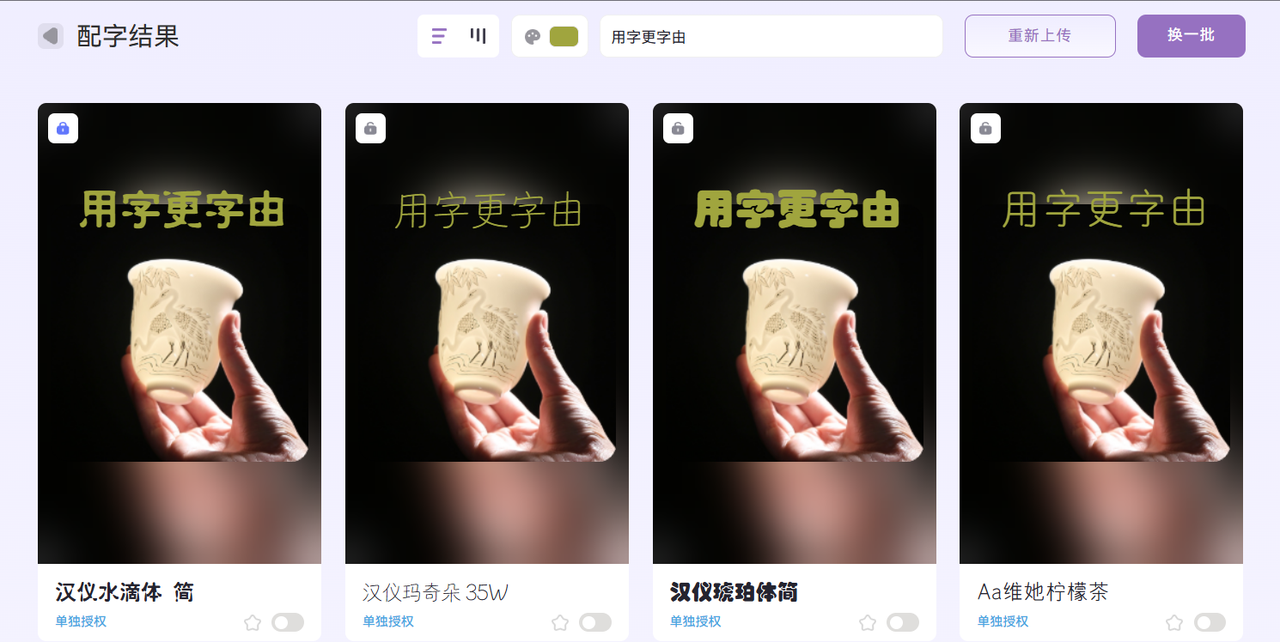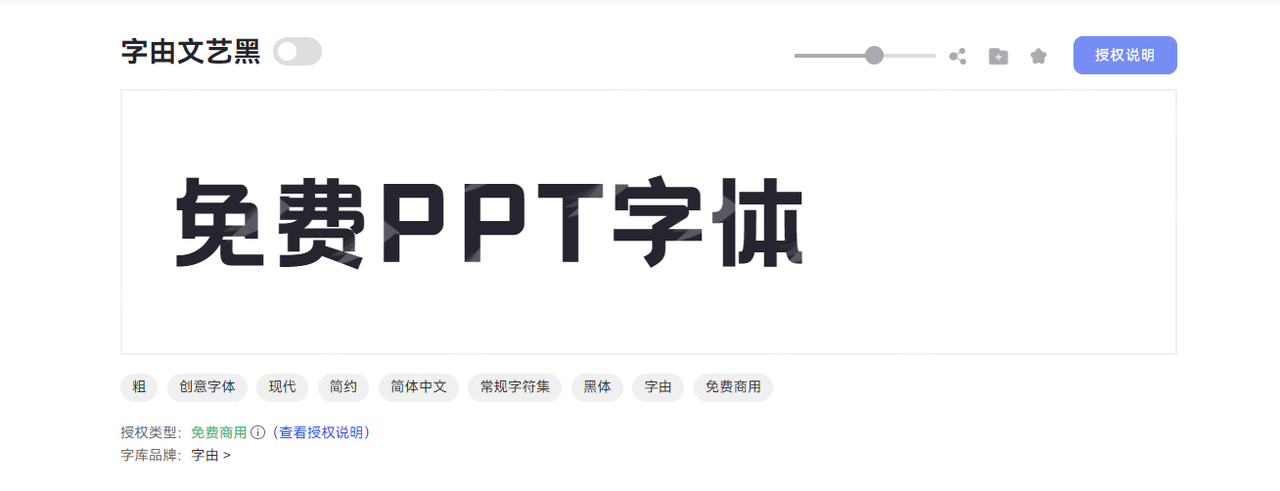
免费 ppt 字体哪里找?6 个高质量字库赶快收藏!
有没有工作中经常需要用到 PPT 的小伙伴?你们是否每次也会头疼怎么能找到默认字体之外的免费 PPT 字体?我们都知道,一款好看且合规的 PPT 字体是提升演示效果的关键因素,和 PPT 主题高度匹配字体会让人看起来更加舒适且有足够的吸引力,候系统自带的字体并不能很好地满足制作 PPT 的需求。不用担心!接下来介绍的这 6 个高质量免费 PPT 字体库赶紧收藏起来备用,涵盖了复古优雅、商务简约、潮酷朋克、创意手写等多种风格,帮助你制作更加高质量且出彩的 PPT。
一、字由
字由是面向设计师用户提供字体应用,管理,授权服务,注册用户超 2000 万的必备字体工具。字由客户端集成了 1000+ 字体厂商公开授权免费商用字体,适合 PPT 的字体也不在少数,保证你用字无忧。
而且字由支持在 PS、AI、ID、XD、Figma、Sketch、CDR 等设计软件中一键应用字体,无需下载,安装字体包,不占用系统内存,即可完成字体应用。
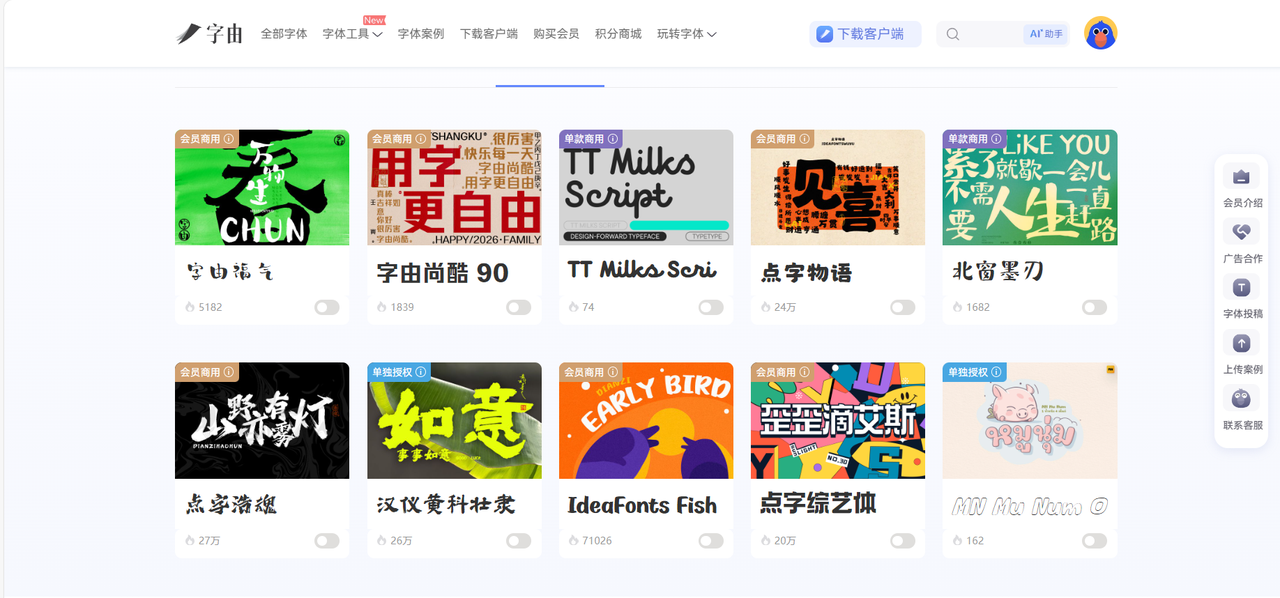
有一个功能是我要强烈推荐的——AI 配字,可以帮助新手小白的你快速选择适合 PPT 风格的免费字体。用户只需上传一张图片,即可通过 AI 识别图中元素,并从海量字体数据中,推荐适合该图片的字体,同时支持对文字样式进行自定义编辑,助力设计师创作。
- 推荐字体:字由文艺黑
字由文艺黑是字由品牌推出的创意黑体字体,以现代简约风格为核心,将图形设计法则巧妙融入黑体设计。字体字形方正饱满,既保留黑体的稳重基调,又通过优雅的艺术弧线处理增强视觉张力,让整体结构充满平衡感与力量感。字由文艺黑笔型设计独具特色,以利落直角勾勒轮廓,搭配方头笔画与均匀粗细,笔画连接采用断开处理,既保持线条的独立性,又让字形更显灵动透气。作为免费商用字体,字由文艺黑字符集覆盖常规中文,适用于商务、党建、科技等风格的 PPT,可以用作年终汇报或者是一些正式的场合,是现代设计中追求文艺感与商业价值的理想选择。
二、DaFont
DaFont 是全球知名的一个免费字体平台,内含 10 万种字体,覆盖了复古、手写、涂鸦、可爱等多种风格,主要提供创意手写体的风格。我觉得 DaFont 的分类是真的很详细,按照风格、主题、语言等多个维度对字体资源进行划分,让你能更快地找到想要的 PPT 字体。或许是因为该平台的字体数量过多,它的质量参差不齐,如果你想要优质的 PPT 字体,得自己好好筛选一下哦。
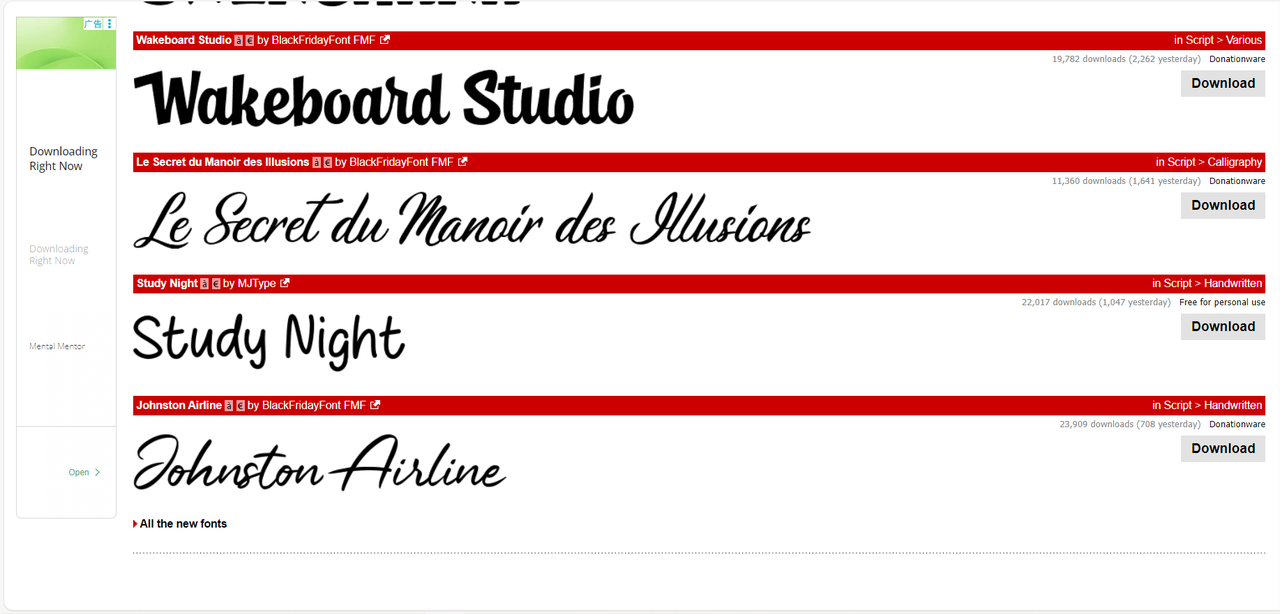
三、Font Squirrel
一直在找商用 PPT 字体的设计师小伙伴们一定要记好了!Font Squirrel 提供大量可商用的免费字体,所有字体均是经过授权审核的,确保可以免费用于个人/商用项目。值得一提的是,Font Squirrel 提供字体下载、Web Font 转换、子集化(减少文件大小)等服务,有需要的用户可以慢慢研究。相较于上面提到的 DaFont,它的字体数量相对较少,只有 1000 种左右,但字体质量更高,设计感很强,不过中文字体选择有限,更倾向于提供英文 PPT 字体。
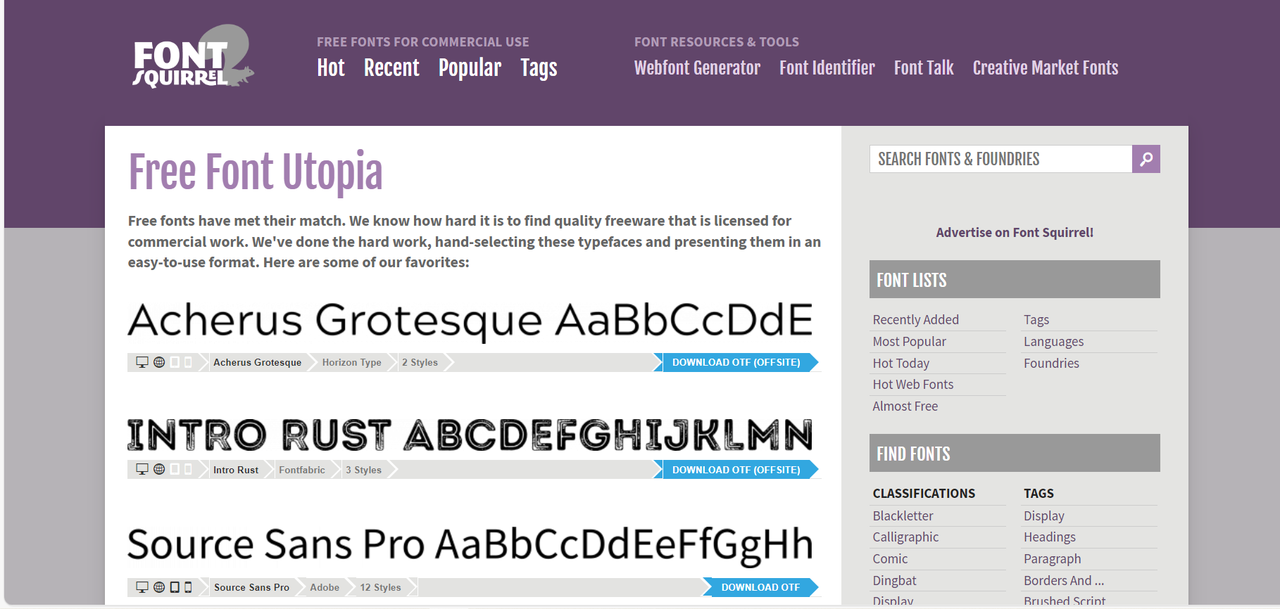
四、Google Fonts
Google Fonts 是谷歌推出的全球最大的开源字体库,所有字体均遵循开源协议,可免费用于个人/商用 PPT 设计,无需付费或授权,还支持直接嵌入 PPT 或本地安装。它拥有中文/英文字体的专区,用户可以根据需求来选择。Google Fonts 的字体筛选一直是我用起来顺手的,根据类别、语言、风格、线条粗细、倾斜角度、字宽的维度来搜索字体,定位更清晰准确,便于快速锁定字体。不过它提供的字体都比较简约日常,如果需要设计感强的字体,这个字库可能不太适合你哦。
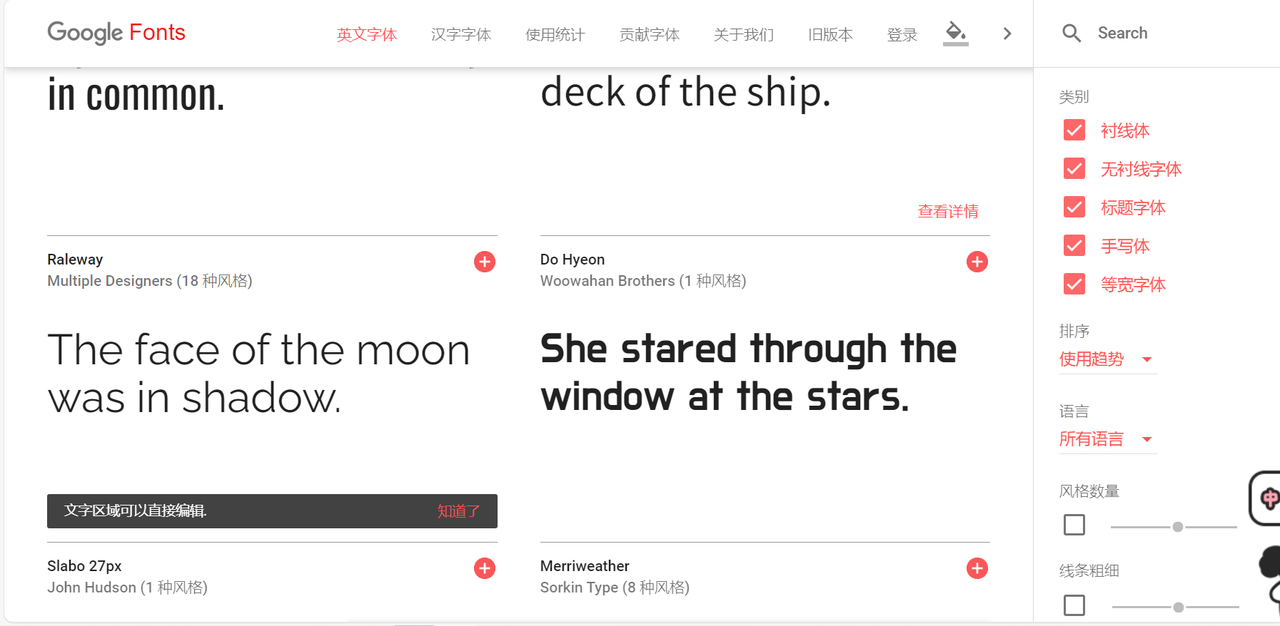
五、Fontspace
Fontspace 也是非常专业的免费商用字库,支持本地安装及 Web Font 使用,可按风格、语言筛选 PPT 适配字体。它专门为涂鸦字体设置了一个版块,包含滴水、纹理、融化、油漆、摇滚等风格,文字效果贴近在城市墙壁、公共建筑等地方的喷涂艺术效果。你的 PPT 做的是和涂鸦艺术、潮酷设计相关的领域,不妨来 Fontspace 找找合适的字体。除此之外,它还设有设计师社区,根据每个设计师的字体被下载数量形成了排行榜,不知道要选择什么类型的字体,可以根据排行榜看看当下比较热门的哦,说不定能提供一些灵感。
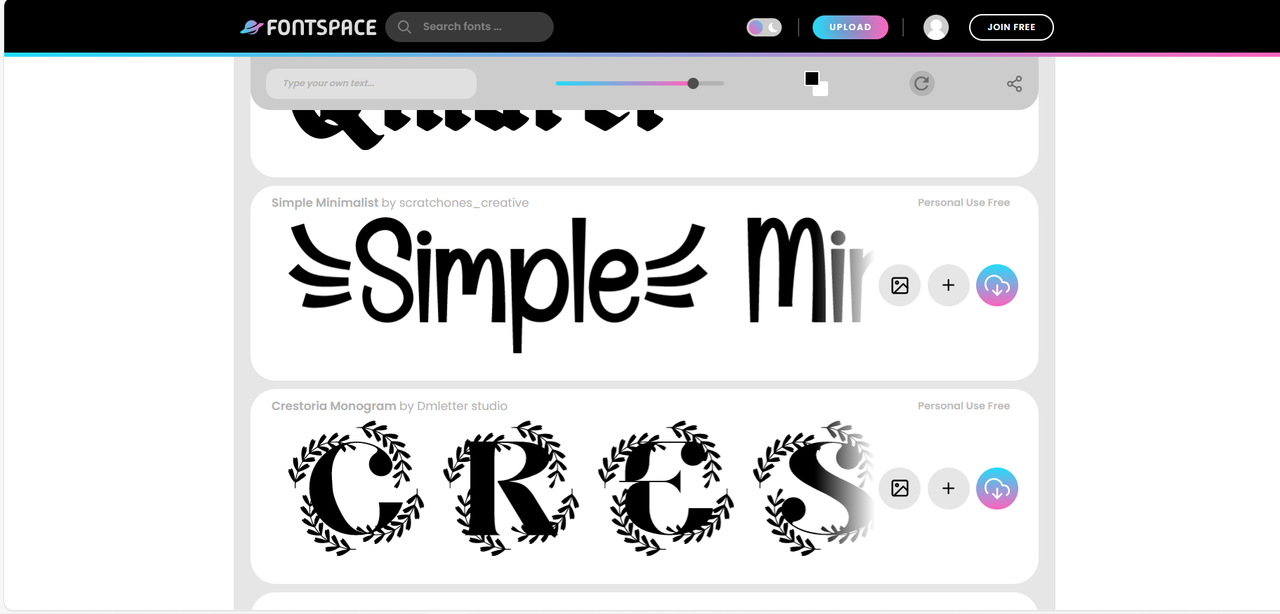
六、Open Font Library
Open Font Library 收录了超 2000 种字体,支持100+语言的选择,完全开源免费使用,无版权风险。它的字体数量不算多,且更新速度较慢,有时候会受到国内网速的限制,出现界面卡顿的问题。我认为 Open Font Library 最大的优势在于多语种小众字体丰富,适合做差异化设计。而且它的字体可免费商用、修改、二次分发,不需要额外授权或署名,自由度很高,开源项目、跨境设计、印刷物料都能放心用。
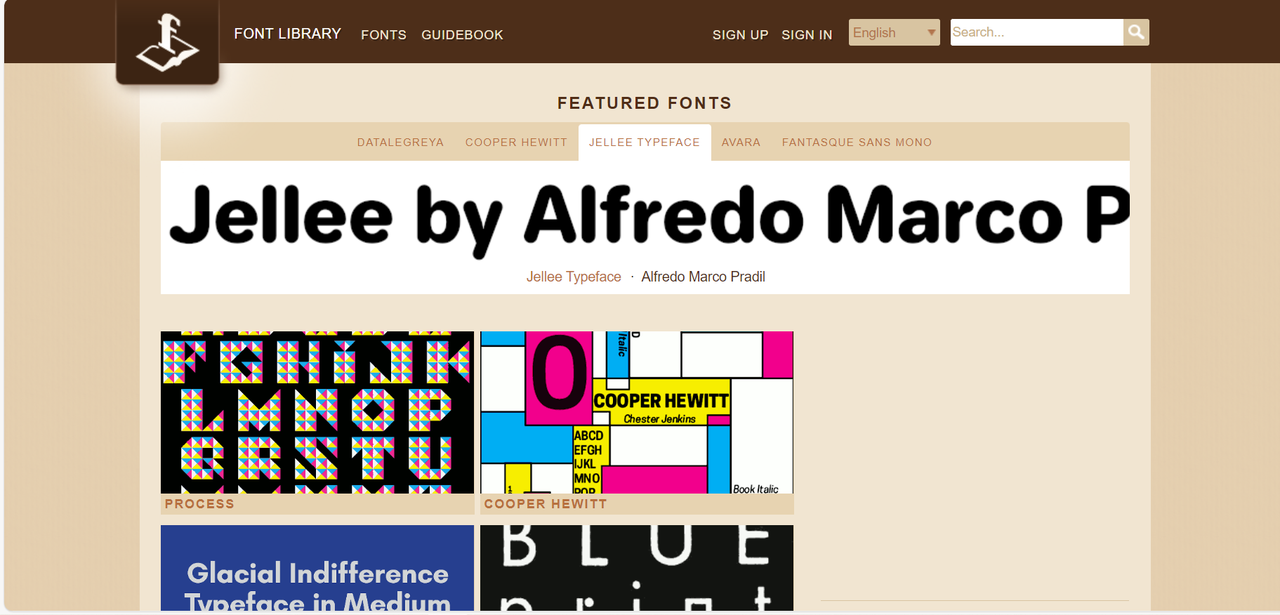
总而言之,关于免费的 PPT 字体库的推荐就到这里了,其实这些字库使用起来都是比较省心的,只是风格上略微有些不同。字由属于授权清晰、字体种类多且有 AI 功能;DaFont 提供创意手写字体,商用较少;Font Squirrel 确保商用无风险;Google Fonts 则适合多语言商务 PPT,Fontspace 的特色是涂鸦字体,Open Font Library 支持开源多语言。大家根据 PPT 主题去选择就好了,不仅能提升 PPT 的呈现效果,还能有效避免侵权问题。